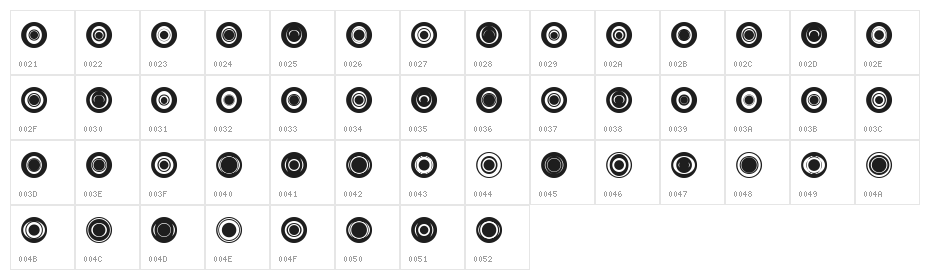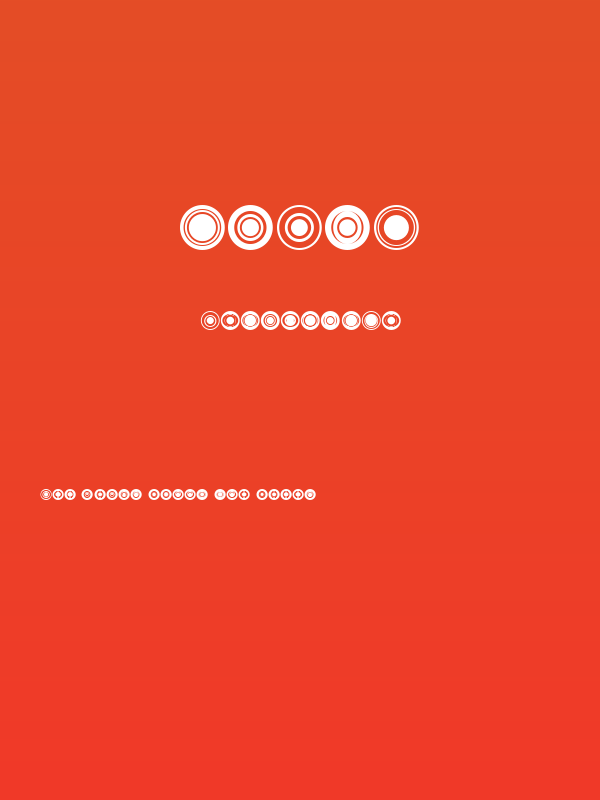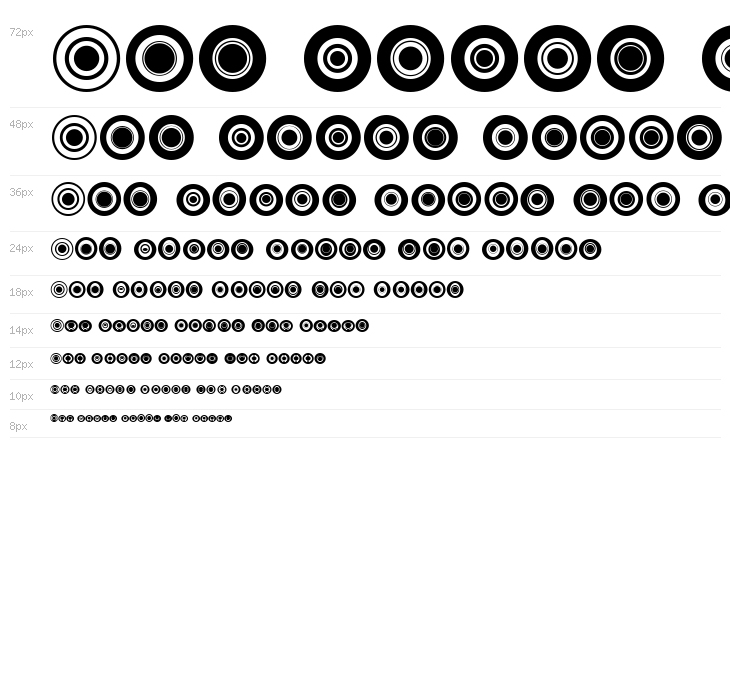
Botan Font
| Caso d'uso | Logos, Headlines, Artistic projects |
| Progetti proposti | Ideal for wedding invitations, eco-friendly product packaging, garden-themed event posters, and artistic branding projects. |